Alphabettes Soup, livro com forte participação brasileira, reúne dez anos de feminismo na tipografia
Capa verde de Alphabettes Soup: um grande A formado por centenas de letras recortadas de vários alfabetos, sobre fundo rosa
Antologia e espécime tipográfico com mais de 100 fontes de mulheres e pessoas não binárias.
O que é
Alphabettes é uma rede de designers de tipos, letristas, tipógrafas e professoras de design. Nasceu em 2015, no meio das discussões sobre sexismo e diversidade de gênero na indústria tipográfica, e passou de 300 integrantes sem apoio financeiro nem estrutura formal. Ao longo da década publicou centenas de artigos, juntou designers iniciantes com mentoras e organizou encontros e sessões de crítica.
O livro nasceu em março de 2024, quando Amy Papaelias, uma das fundadoras da rede, levou a ideia a Nina Paim, que tinha acabado de abrir a Bikini Books. Foi impresso na Gráfica Maiaduoro, em Portugal, em 1º de abril de 2026, e teve lançamento informal no dia seguinte, na sede da editora, em Porto.
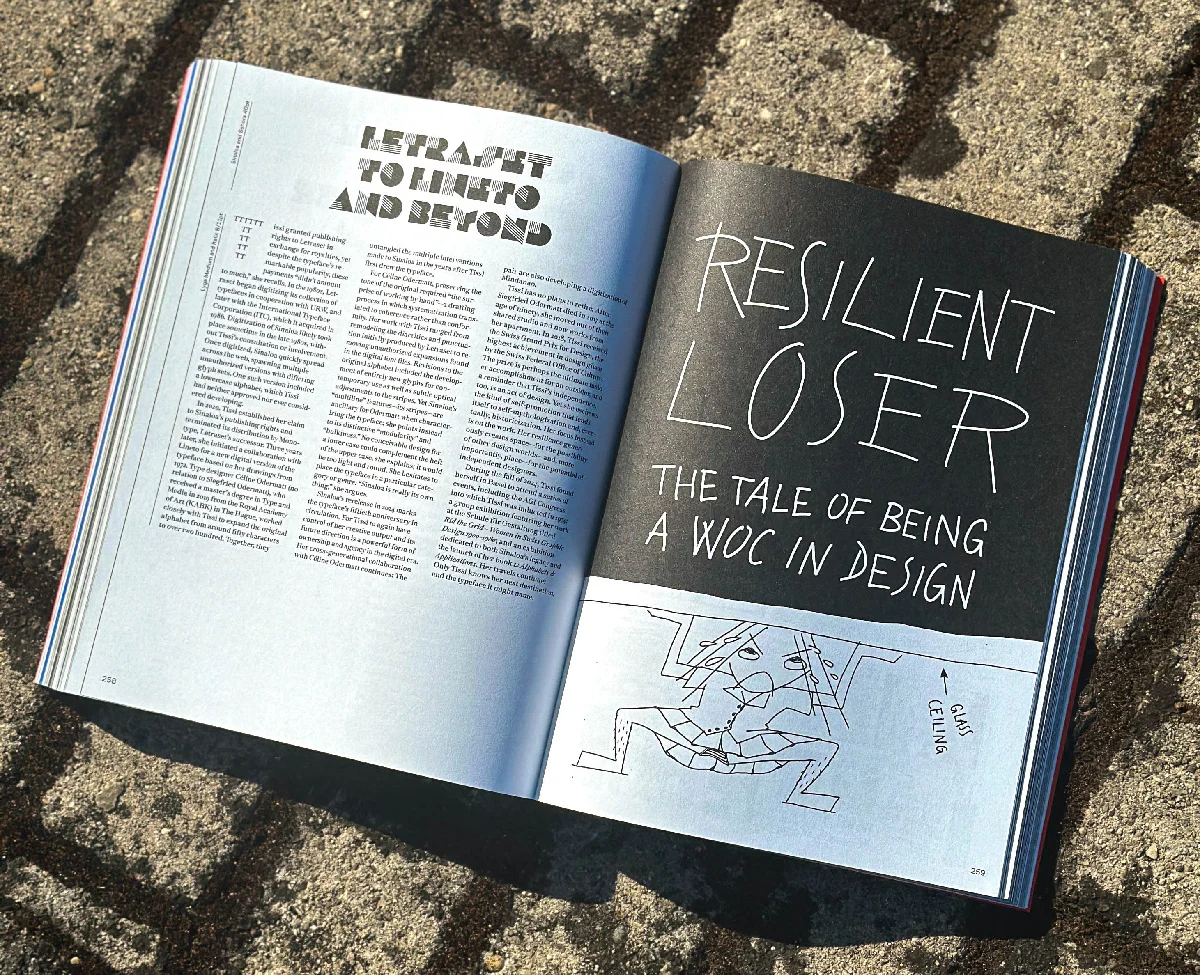
Livro aberto numa página preta com o título Resilient Loser: the tale of being a WOC in design, em letras desenhadas à mão
Sobre o que trata
A editora descreve o livro como uma década de abordagens feministas para pesquisa, design e construção de comunidade em tipografia. Junta artigos publicados no site da Alphabettes com ensaios inéditos, entrevistas com integrantes, histórias visuais e balanços de iniciativas da rede. Os temas cruzam cultura, língua, práticas de negócio, tecnologia e tipos.
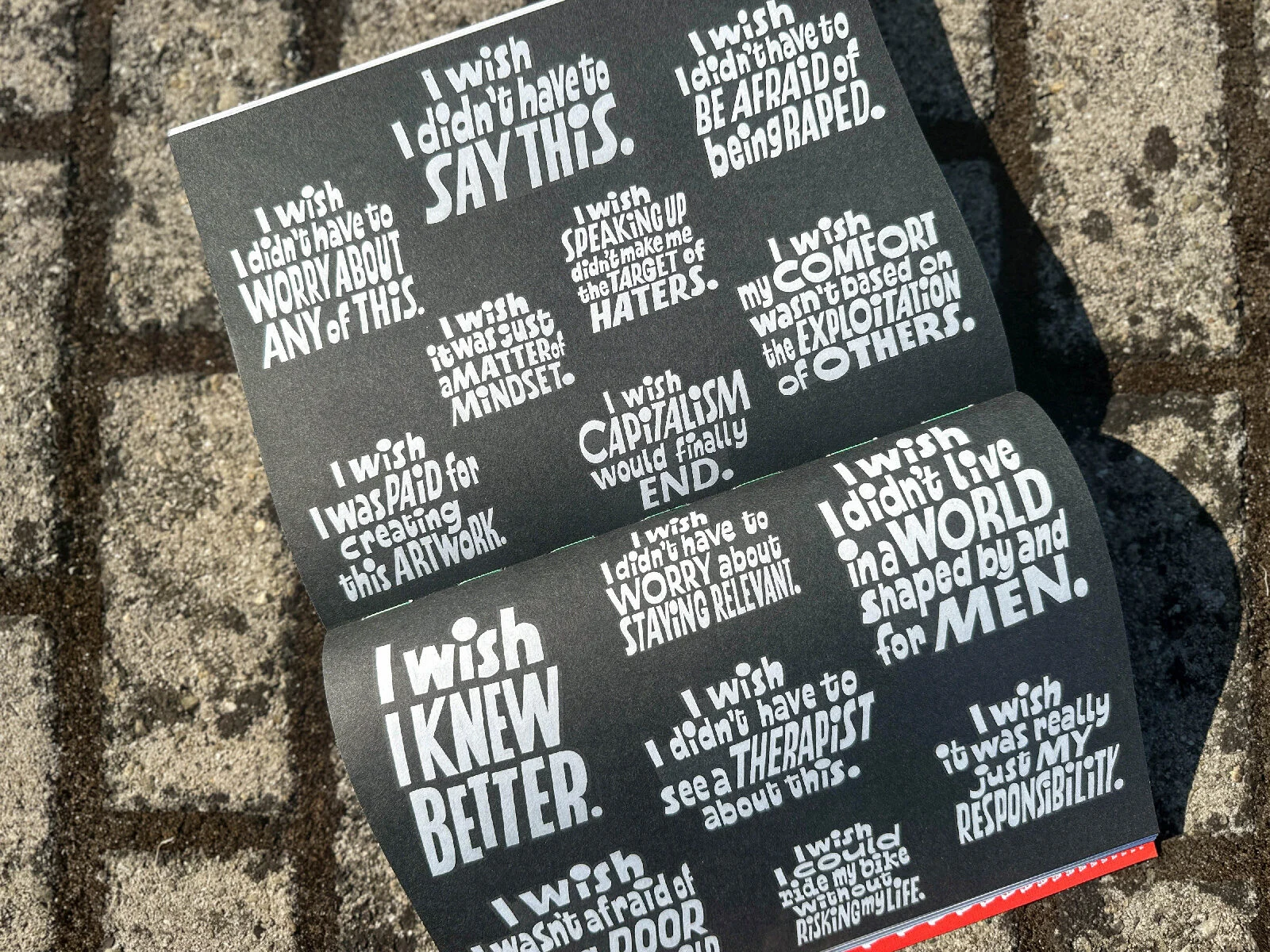
Páginas pretas com frases em lettering branco que começam com I wish, como I wish I knew better
O livro foi pensado também como espécime. A regra de composição, anunciada no post de pré-venda da rede, era uma fonte por designer, usada uma única vez. A editora fala em mais de 100 fontes de mulheres e pessoas não binárias; o post de 2025 falava em mais de 120. A capa, segundo Papaelias, foi montada por Tereza Bettinardi a partir de centenas de glifos.
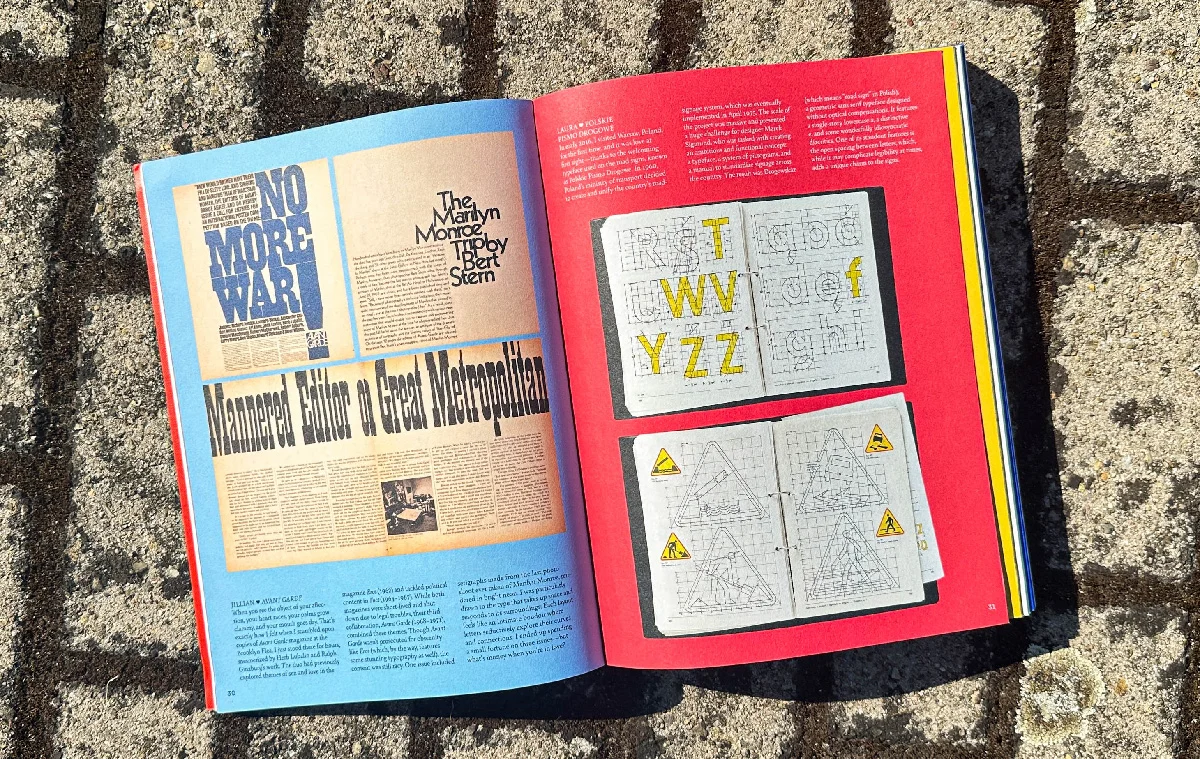
Livro aberto em páginas azul e vermelha, com recortes de impressos antigos e cadernos de desenho de letras
A participação brasileira
Nina Paim, designer, curadora e editora brasileira, fundou a Bikini Books em 2023 e coordenou o livro. O design é do Studio Tereza Bettinardi, de São Paulo, com assistência de Guilherme Mohr e Lou Huguenin. As ilustrações são de Vitória Bas, ilustradora e designer de São Paulo. Entre as autoras está Marina Chaccur, designer de origem brasileira que dá aulas na Royal Academy of Art, em Haia.
O prefácio é de Teal Triggs, e a preparação de texto, de Caren Litherland.
A ficha da editora e a da Slanted dão 384 páginas. No post de lançamento, a própria Papaelias descreve o livro como de 400 páginas.
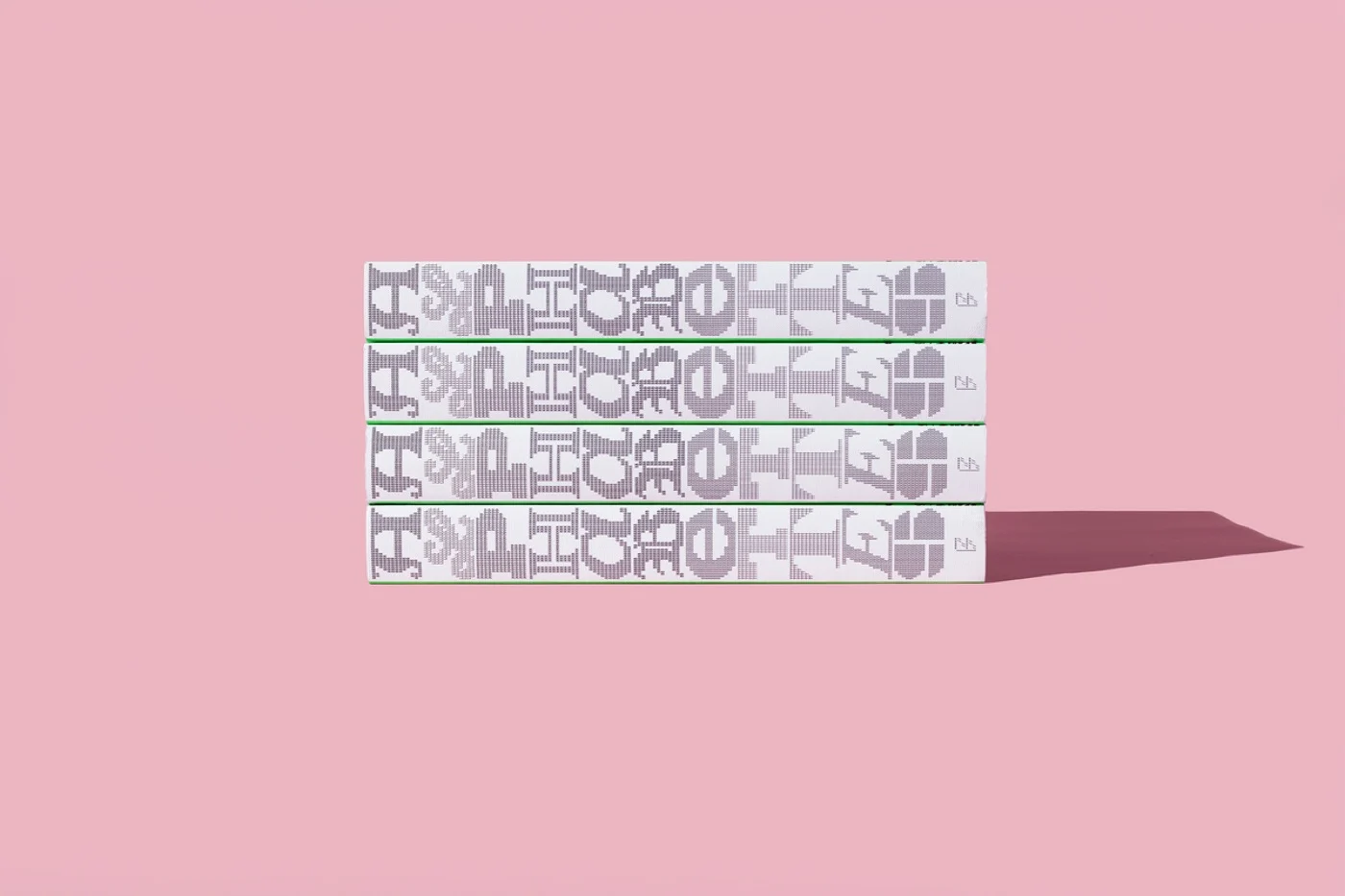
Quatro exemplares empilhados mostrando a lombada branca com o nome Alphabettes em letras pixeladas
Para quem interessa
Para quem desenha tipos ou letras, estuda história da tipografia ou organiza comunidades de design. Serve também como catálogo de mais de 100 fontes de mulheres e pessoas não binárias, cada uma usada uma vez.